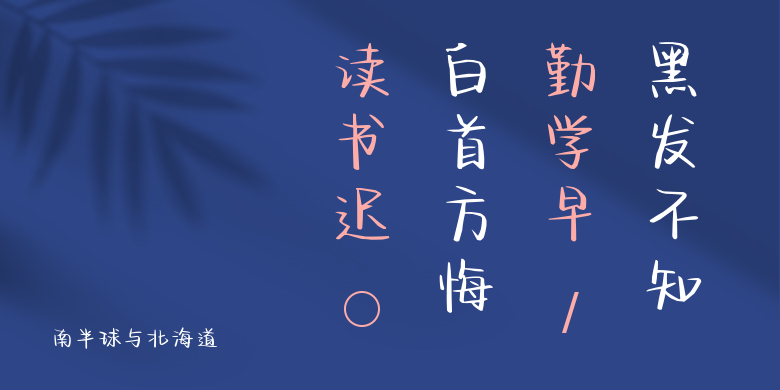
南半球与北海道
南半球与北海道,这款字体结构工整、笔画清晰,兼顾美观与易读性,适用于标题、正文、海报、包装、LOGO 等多种场景。字形优雅稳定,风格百搭耐看,适配日常排版与创意设计,让文字呈现更舒适、更具质感。南半球与北海道一笔一画,皆是细节,以均衡的比例、流畅的线条打造舒适视觉体验,字形端正大气,风格简约现代。无论是商业设计、品牌宣传还是日常排版,都能轻松驾驭,让文字更有格调与力量。南半球与北海道字体下载。